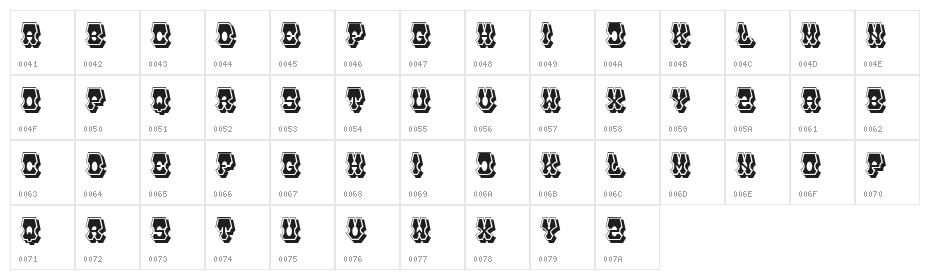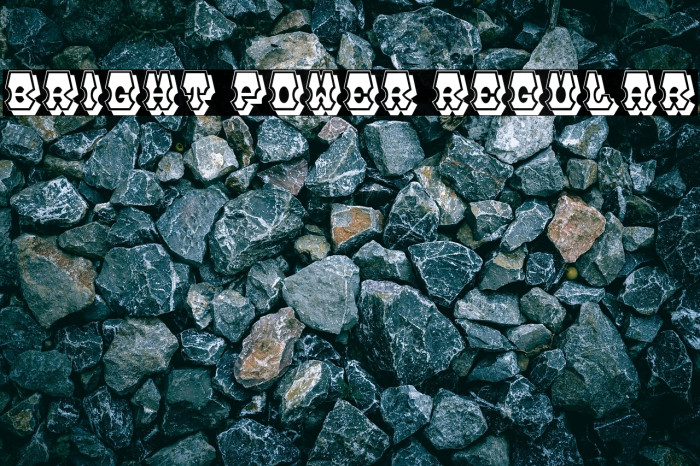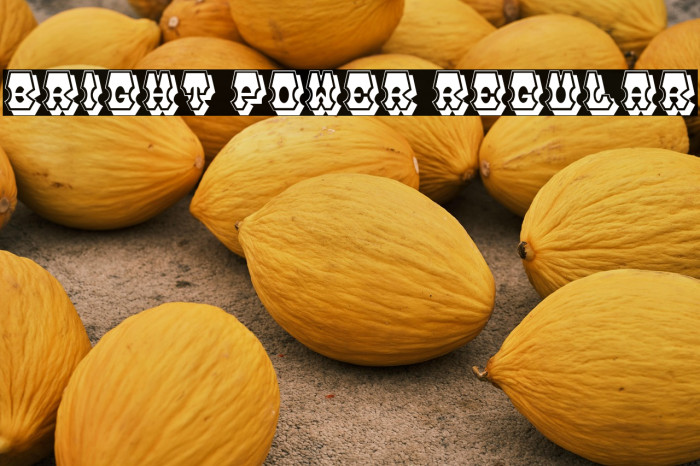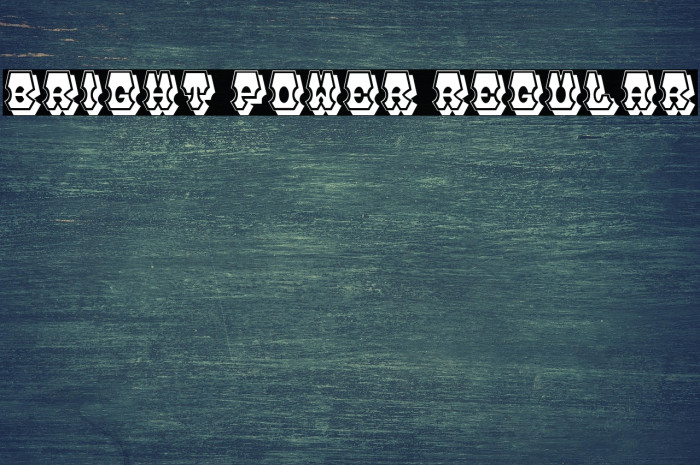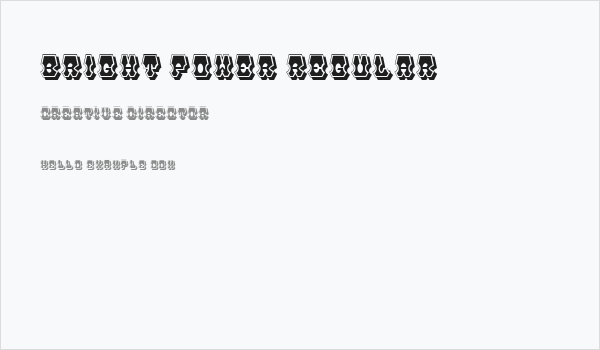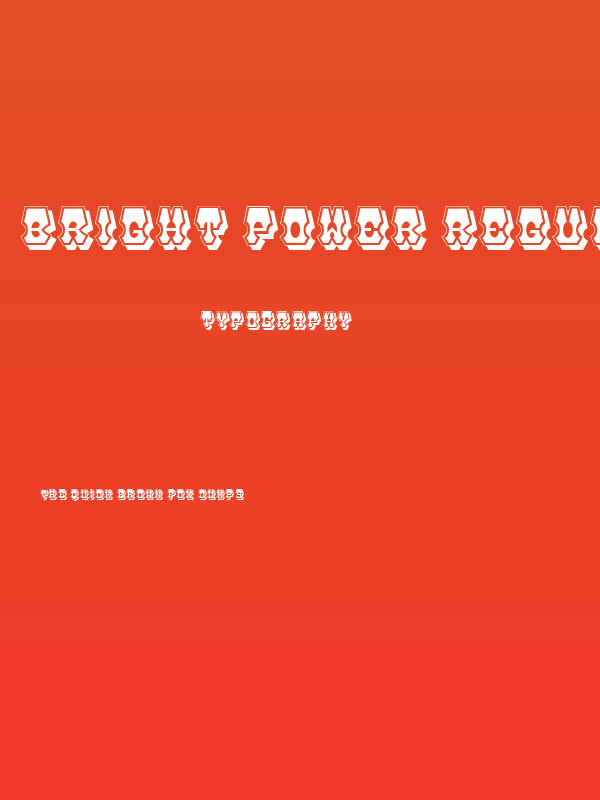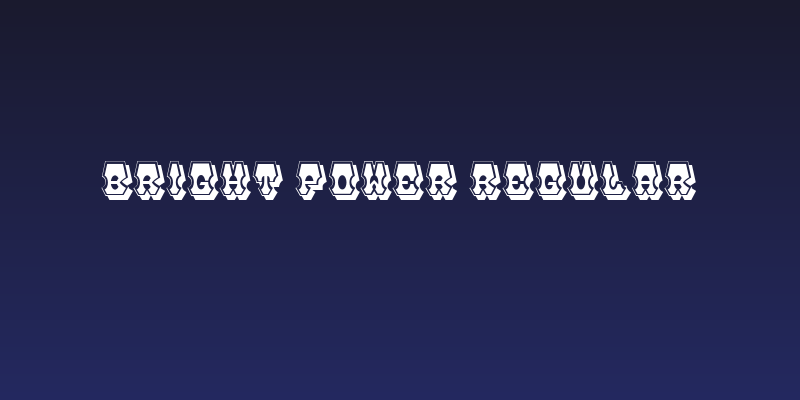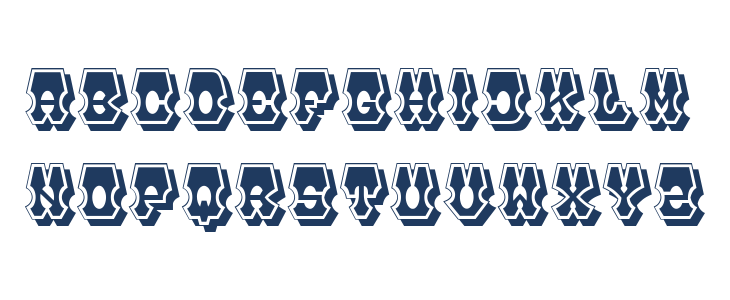
Bright Power Regular Font
| Progetti proposti | Ideal for posters, logos, video game graphics, and any project needing a bold, eye-catching typeface. |